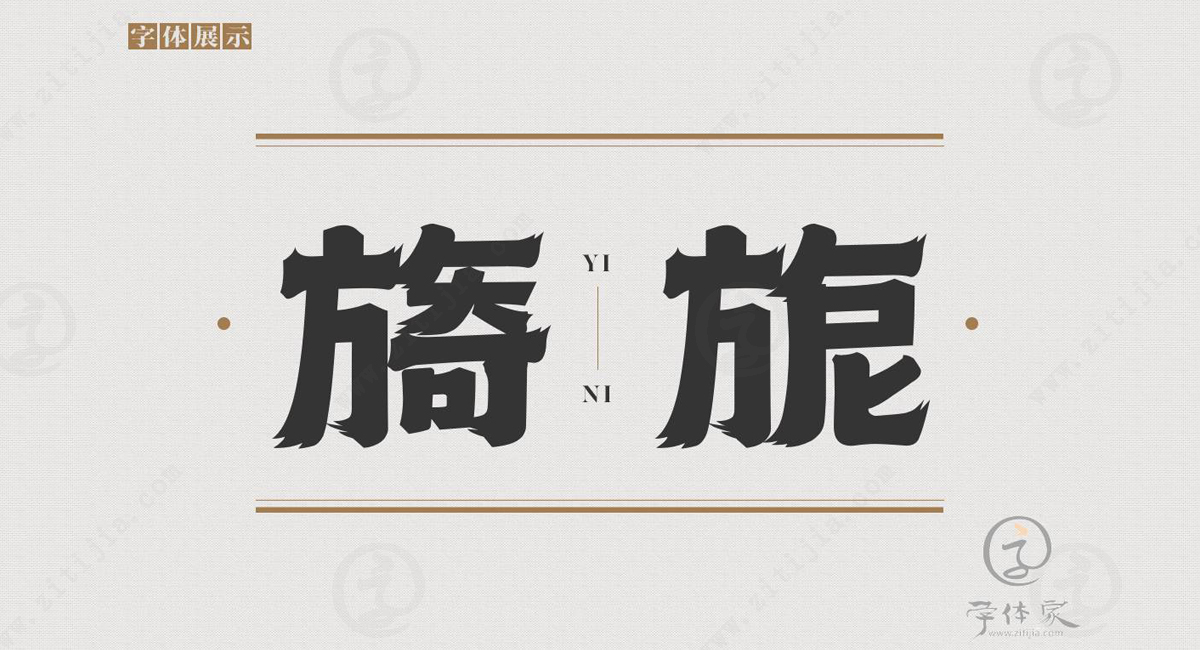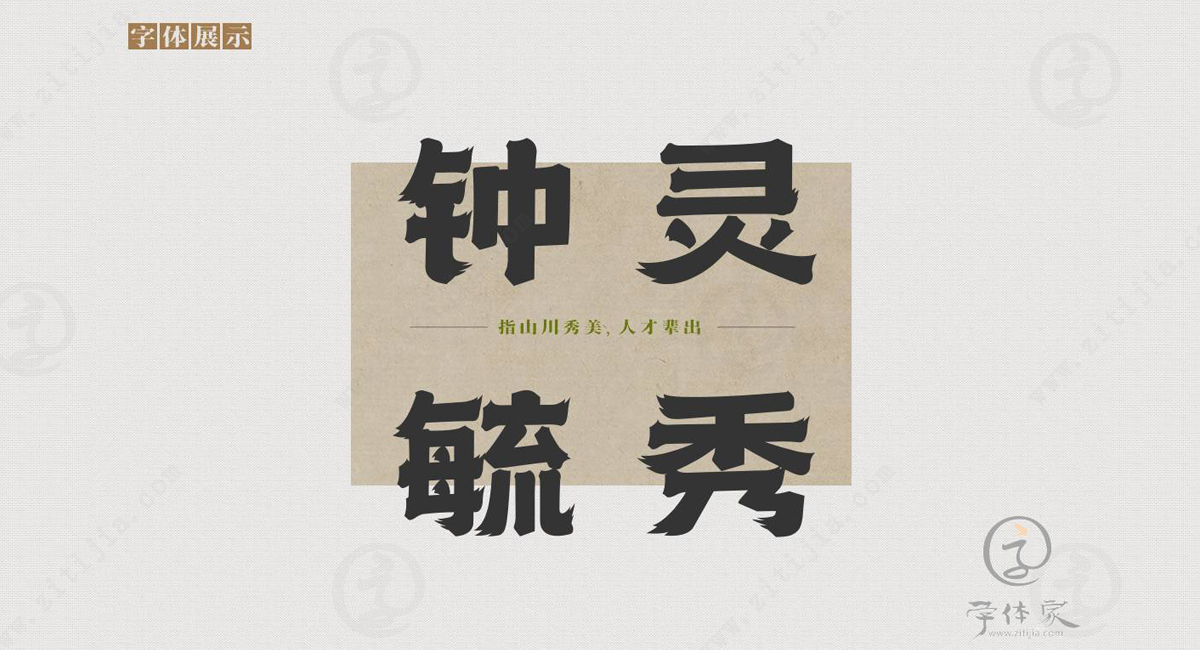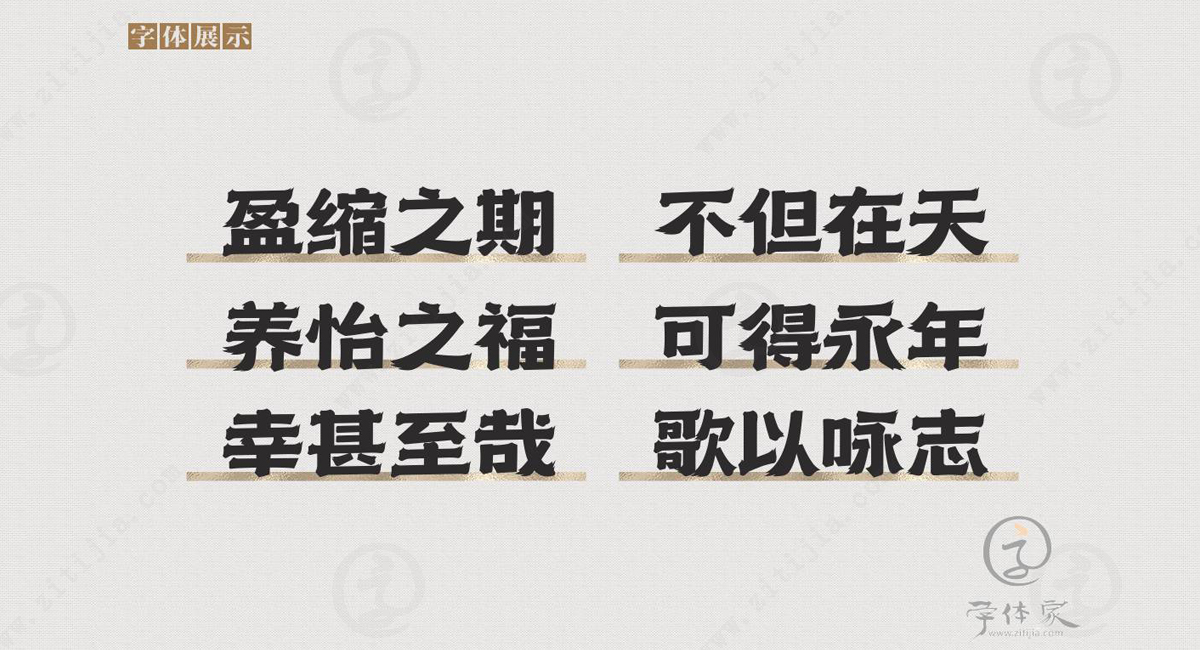
自然元素与现代设计地结合,字体家网站上首青柏体字体欣赏
上首青柏体,一款独具特色的字体,将自然元素与现代设计巧妙地结合起来,形成了一种既有原始野性力量又不失简约大方的风格,是现代高端设计中不可或缺的重要组成部分。该字体由上首造字字库制作出品,已在字体家网站上合作发布。
风格特色
这种字体以整齐方正为其特色,字体笔画粗细均匀,线条流畅自然,给人以干练有力的感觉。与此同时,上首青柏体还融合了许多原始元素,如山林、河流、石头等,增加了字体的野性和粗犷之美。这种特殊的设计风格,使得上首青柏体在众多字体中脱颖而出,成为了商业广告、海报字体以及品牌标志等高端产品的不二之选。
作品呈现
上首青柏体的精细之处在于将一些原始元素与现代设计相融合,呈现出一种独一无二的风格。从字体的整体设计到每一个笔画间的间隔,都透露出一种精密而不失豪放之美。同时,上首青柏体还有着出色的可读性,无论是在广告标语中还是在其他类型的设计作品中,都能够得到最好的呈现效果。
无论是在品牌推广、广告宣传还是各种商业活动中,上首青柏体都是一个不可忽视的资源。通过使用这种字体,设计师可以将自然与现代相结合,呈现出一种独一无二的视觉效果。作为一款高端的字体,上首青柏体拥有着出色的质感和设计感,使其成为了广告设计领域不可或缺的元素。
字体价值
总之,上首青柏体是一款独具特色的字体,它融合了自然元素和现代设计的精华,打造出一种独一无二的风格。无论在品牌标志、广告宣传还是各种商业活动中,利用上首青柏体都能够给设计带来出色的效果。